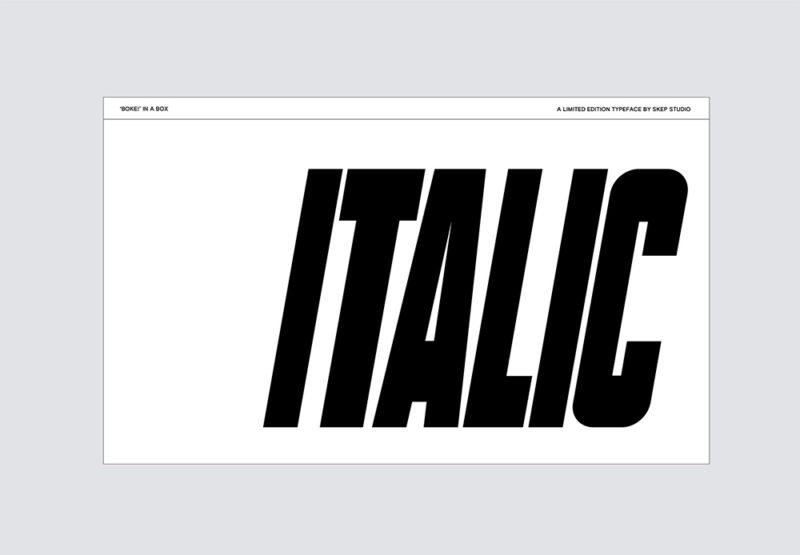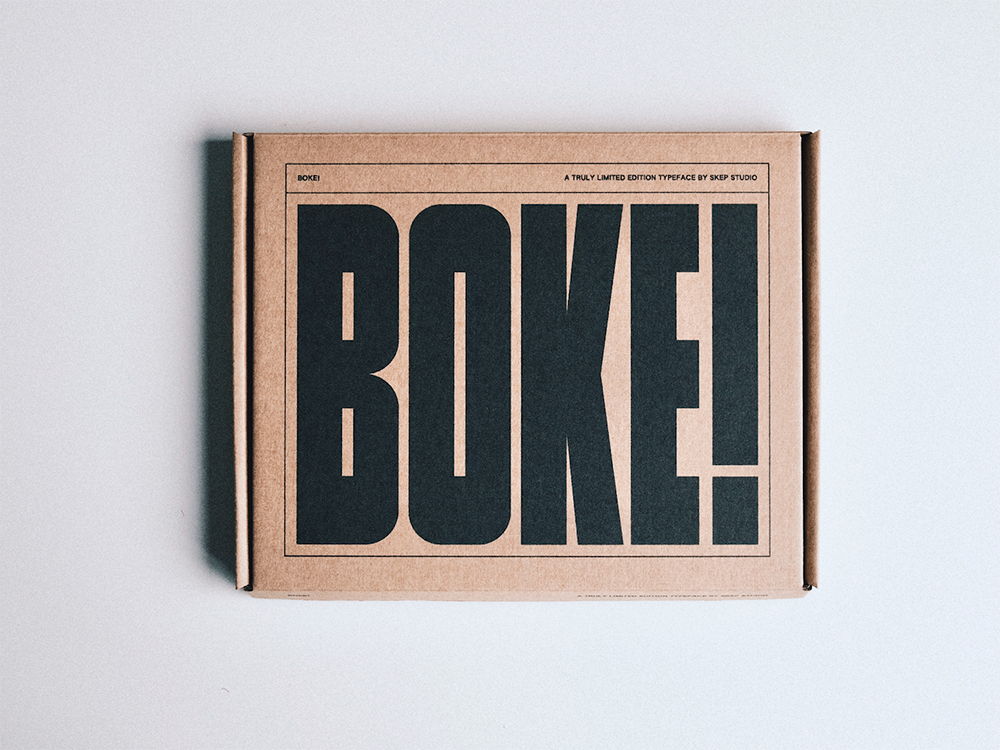
Identidad, packaging, marketing,… un proyecto impecable
Los diseñadores británicos Chris Smyth y Josh Hailes, socios fundadores de Skep, sacuden el tablero con un proyecto tipográfico donde los remates, modulaciones o perfiles de cada tipo —todos de gran calidad—, no son ni de cerca, su único atractivo.
Se trata de Boke!, una familia robusta, pensada para titulares o logotipos, compuesta de solo un peso y un estilo (itálica), que destaca en un primer visionado por su grado de agresividad, resultado de una apuesta descarada por una arquitectura simplista —en términos geométricos— pero ciertamente efectiva.
Por supuesto, Boke! no termina aquí, todo lo contrario. La iniciativa de Smyth y Hailes se construye conceptualmente —y literalmente— como una edición limitada gratuita. En una caja de cartón natural con apenas etiquetados, se encuentra un pen drive metalizado, desde el cual, con ayuda de una clave secreta, los afortunados que pudieron hacerse con algunas de las 50 unidades que fueron puesta a disposición de la comunidad, podrán descargarse las fuentes. Brillante.
En un mundo donde la universalidad digital lo domina todo al ritmo de la inmediatez, Chris Smyth y Josh Hailes han conseguido sorprender con un producto a medio camino entre lo online y lo offline, y seducirnos por su condición de exclusividad.